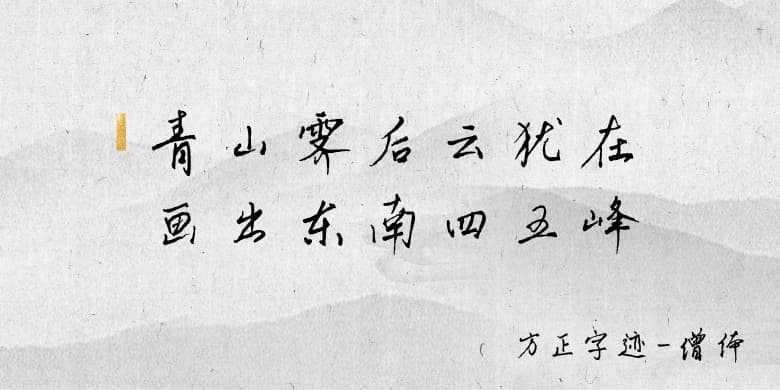
方正字迹-僧体
方正字迹-僧体:古意盎然、 朴拙隽永,当书写成为奢求时,僧体字犹如心中田园的耕耘和期盼,从静心、依禅意,指尖流出意念之美,美而有字,字字有言。
作者少年时,师从家父,酷爱书法,临赵孟頫墨迹,尤有心得。稍长,因学习、工作需要,擅以硬笔临大家碑帖,形成风格,1984年成为中国硬笔书法研究会西安分会会员。其一生,好写字,善琢磨,笔耕不辍。